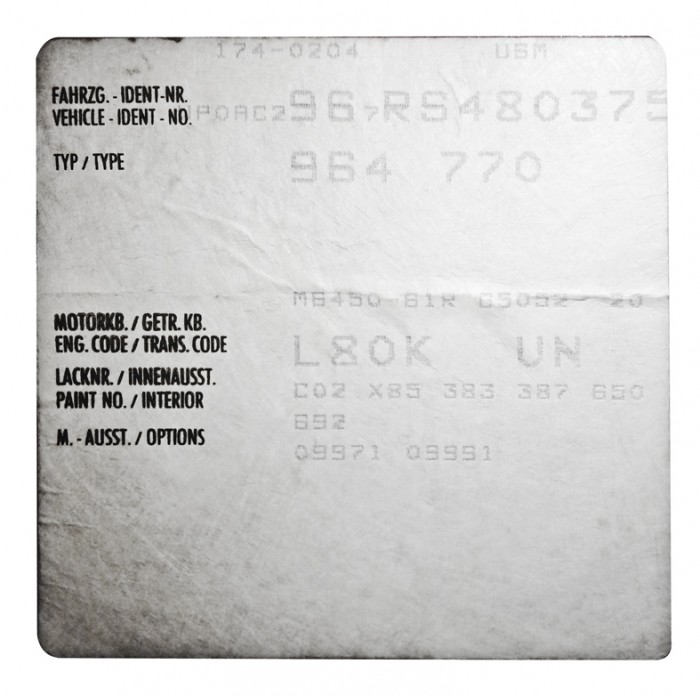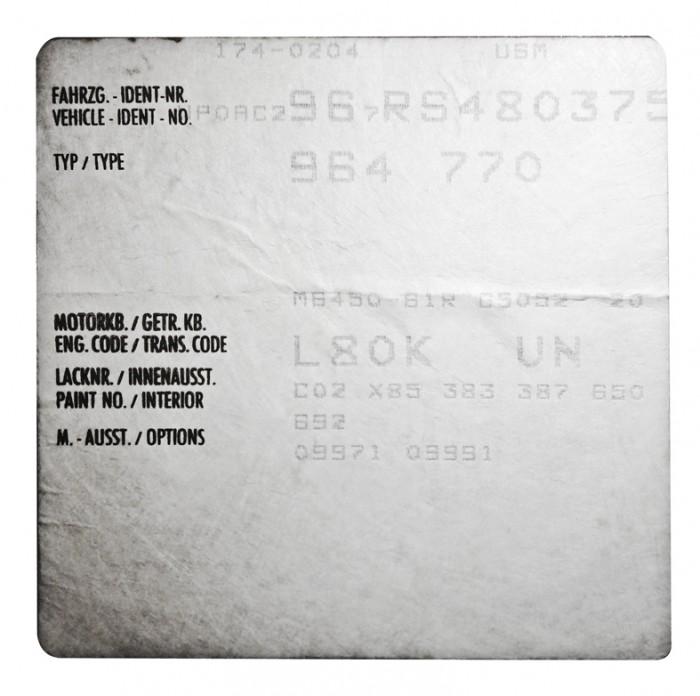
Fonts gesucht (Fahrzeugdaten)
ich muß diesen Aufkleber nachbauen. Hat jemand eine Idee um welche Schriften es sich hier handeln kann?
Die rechten im Bild sind üblicherweise Schriften, die von den Druckerherstellern kreiert und für den jeweiligen Drucker optimiert wurden. Die wird es nicht als verfügbaren Font geben.
Das habe ich mir schon gedacht. Irgendeine Idee, welcher Font diesem nahekommt? Sonst wird's mit meiner Fälscherkarriere wohl nichts mehr  :party:
ja, die OCR-Schriften habe ich schon ausprobiert. Der Knackpunkt sind die 3 und die 8. Aber wenn's gar nicht anders geht...